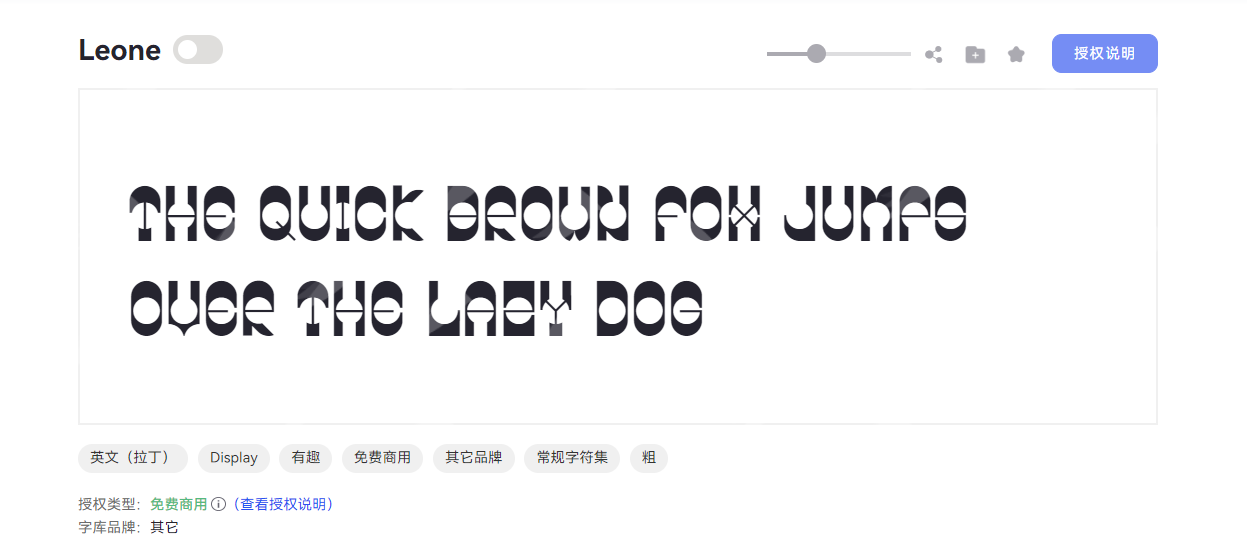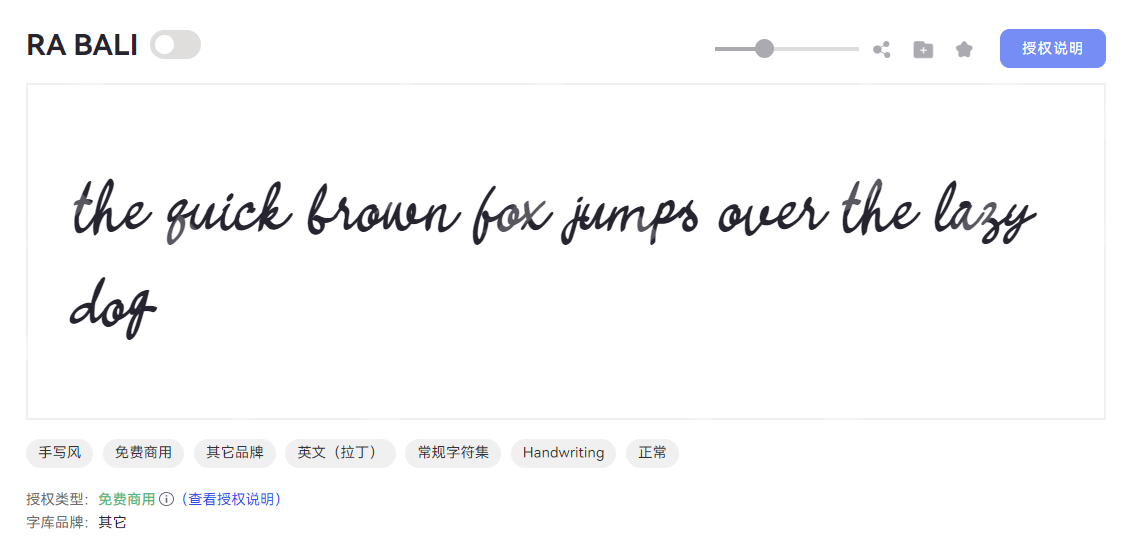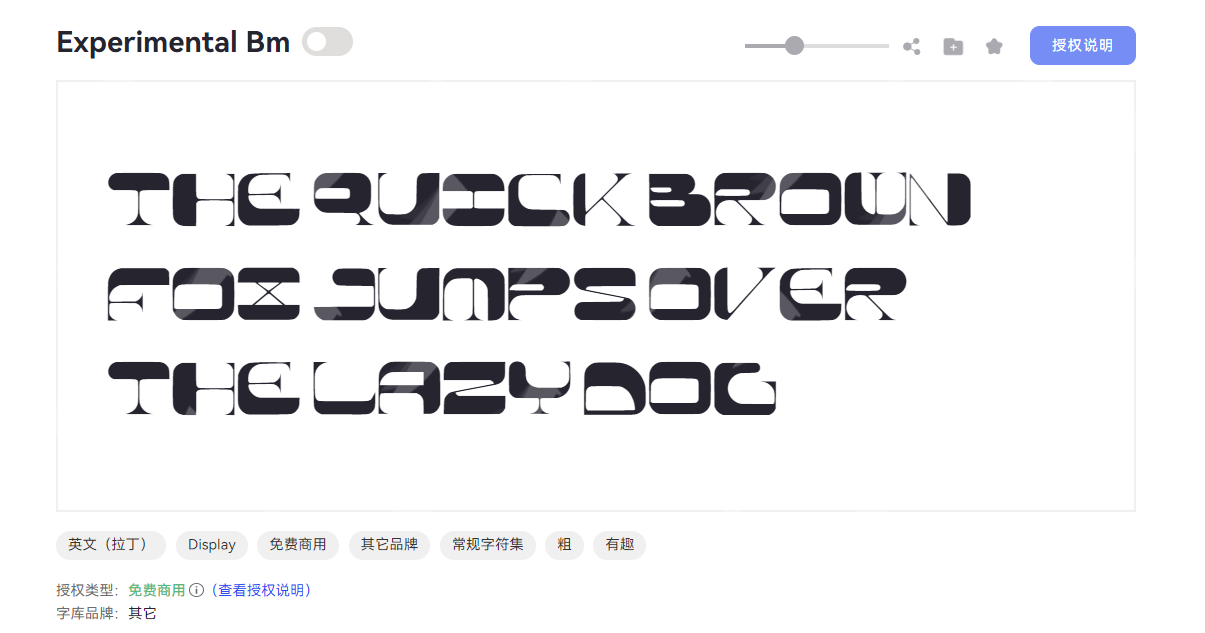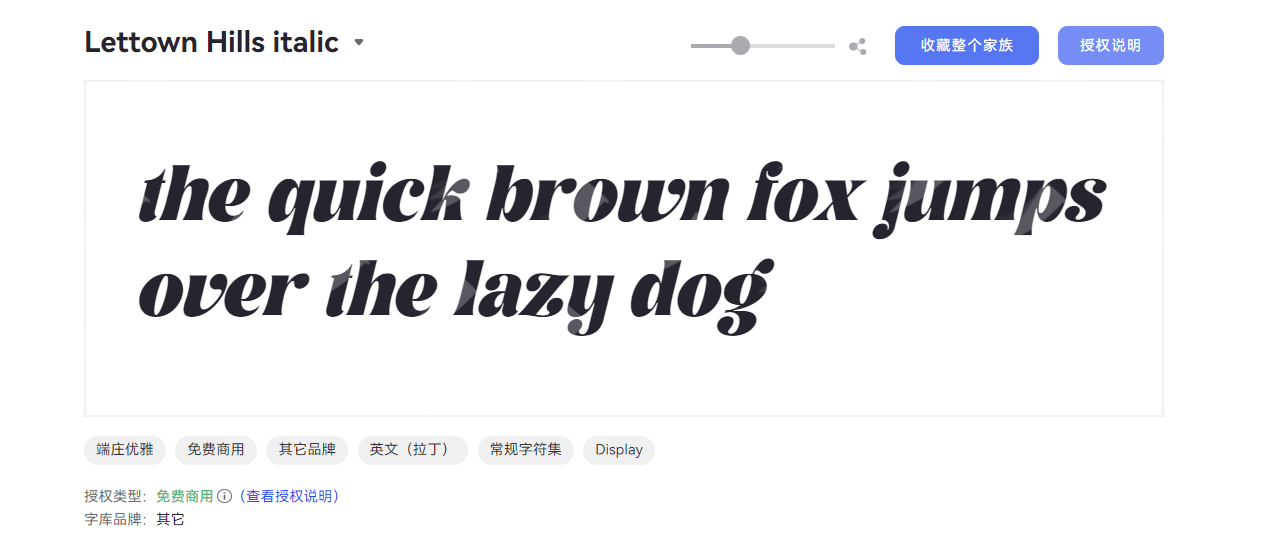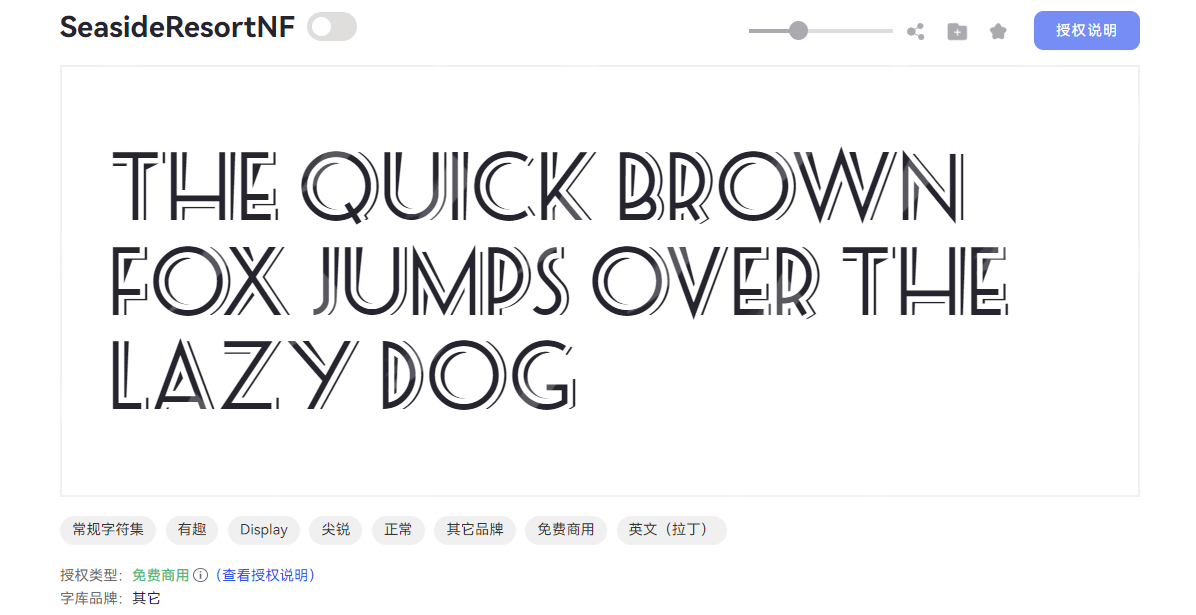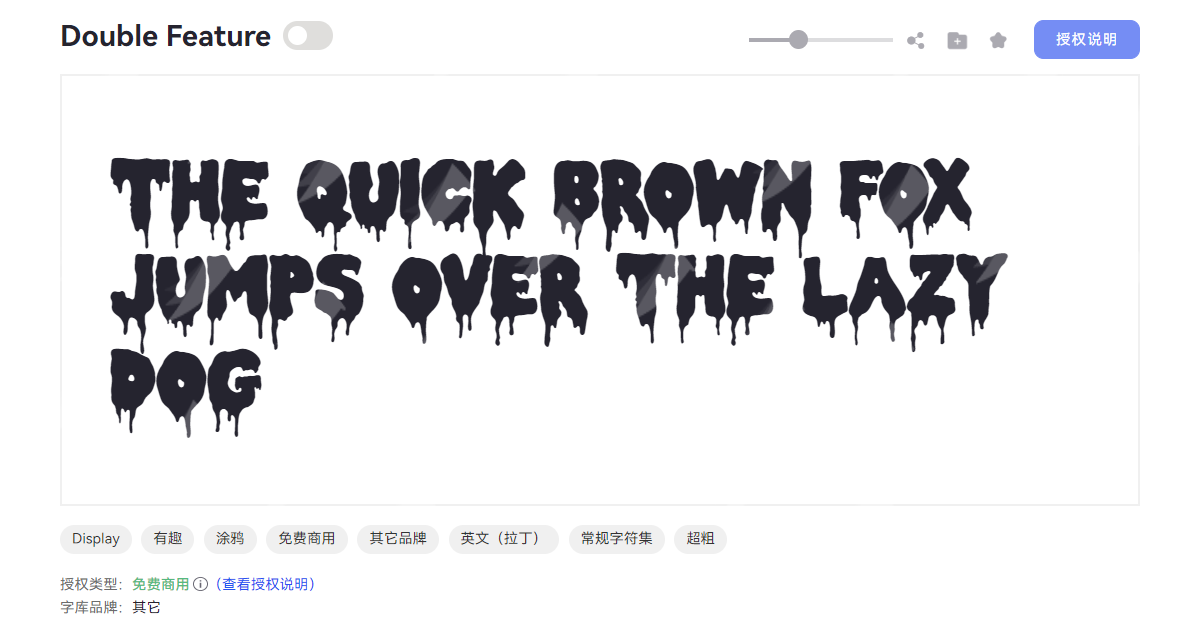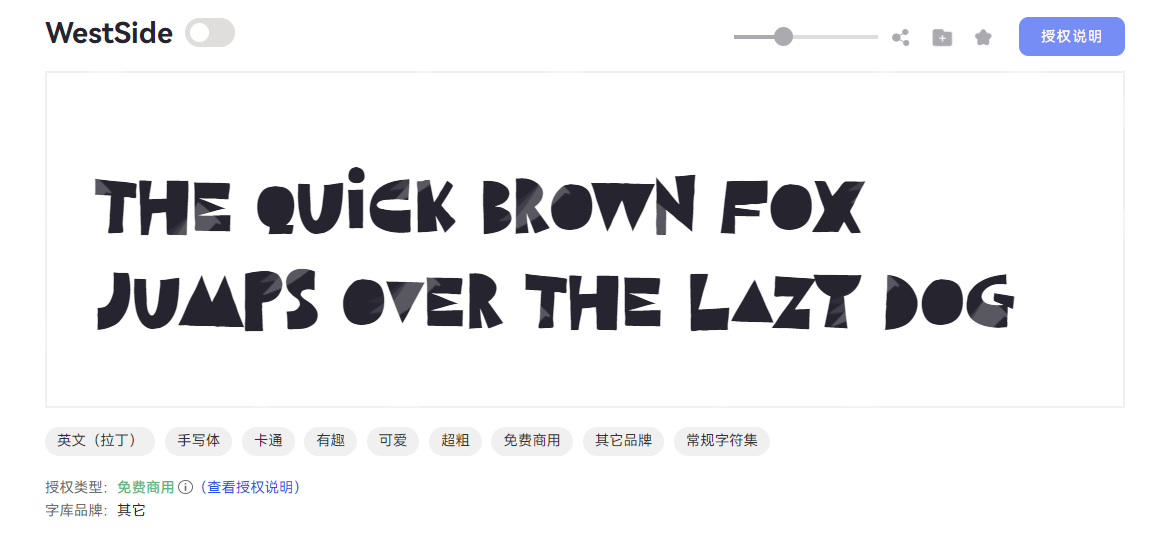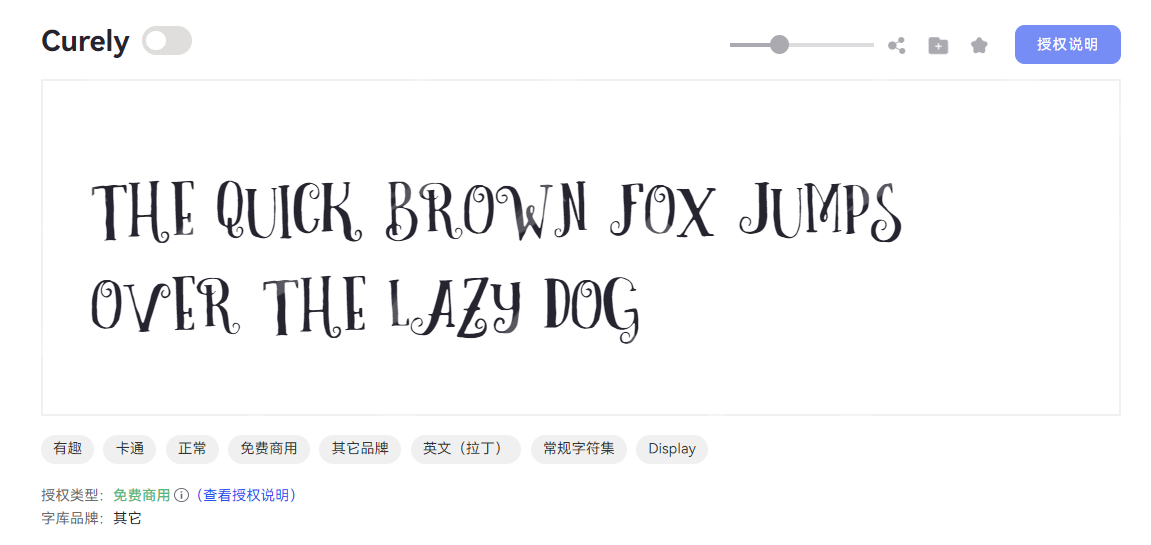
英文艺术字是提升视觉质感的关键因素,通过流畅的笔触和装饰性设计,能增加作品的艺术感。一般来讲,我们在进行海报设计的时候,经常会在中文标题附近穿插一些英文艺术字,用来平衡画面的布局,让海报看起来更具层次感和文艺感。如果你最近也在寻找英文艺术字的资源,千万不要错过我们这份英文艺术字大全!结合字由官网的正版字体资源,给大家整理出了 2026 年最热门的 8 款免费英文艺术字,从新手小白到资深设计师都能直接用,让你的作品瞬间出彩!
1、Leone
字体风格:一款充满趣味感的英文 Display 字体,既大气又不失灵动。
设计特点:修长的字型搭配宽博中宫,让字符在保持粗重笔感的同时,兼具舒展的视觉张力与稳定重心。 最关键的是笔画设计暗藏巧思,粗重均匀的线条以圆润笔触收尾,细节处融入精致装饰元素,笔画连接处的断开处理则打破传统结构,为字体增添几分俏皮趣味。
适用场景:品牌logo、海报设计、创意标题、赛车展览。
2、RA BALI
字体风格:是一款极具个性的英文手写风字体,视觉上给人优雅大气的感觉,以独特的设计细节和实用属性在众多字体中脱颖而出。
设计特点:字形修长舒展,重心稳定居中,中宫松紧适中,既保留手写字体的灵动随性,又保持结构上的平衡感。 RA BALI 在笔型设计上融入了独特的斜切工艺,搭配圆润饱满的笔画端头,让每一笔都兼具利落锋芒与柔和质感。 值得一提的是,该字体的笔画采用断开式连接设计,还原了手写时自然的停顿与呼吸感,同时笔画清晰,避免了可能带来的字体干扰。笔画粗实有力,过渡均匀自然,即使在小字号排版中,也能保持清晰的轮廓与扎实的视觉张力,轻松为设计注入温暖亲切的手写温度。
适用场景:文艺海报、咖啡品牌包装、社交媒体配图、复古信件。
3、Experimental Bm
字体风格:是一款充满个性的英文 Display 字体,,展现出满满的鲜活表现力,吸睛效果很好。
设计特点:字形修长舒展,重心稳定居中,排版整体紧凑有序,视觉平衡感突出。 Experimental Bm 尤其在笔型设计上大有来头,方头笔画搭配利落斜切处理,局部笔画采用“断开”结构,赋予字符灵动跳脱的视觉节奏,细节处的斜切棱角则增添设计温度,让文字成为画面中的趣味焦点。字重饱满粗壮,但某些笔画又极细,看似对比鲜明,杂乱无章,实则展现了强烈的视觉冲击。
适用场景:潮流品牌 logo、潮玩包装、酷炫文创、赛博朋克风海报、游戏背景。
4、Lettown Hills
字体风格:是一款英文手写字体,以端庄优雅的风格立足设计领域,是兼具美感与实用性的最佳选择。
设计特点:从字形结构来看,修长的字型形态搭配宽博的中宫设计,让字体保持舒展大气的视觉效果,确保了基础的阅读清晰度。 笔型设计上,Lettown Hills 圆头笔画的柔和与断开的连接方式形成巧妙对比,圆头笔触增添了字形的温润质感,断开的笔画连接则减少了视觉干扰,让字符在精致中透着利落。而且它拥有均匀的笔画粗细,进一步强化了整体的简约气质,没有繁复的装饰,更能显出现代设计的高级感,是追求个性与实用性平衡的理想之选。
适用场景:电影字幕、vlog 片头、品牌标识、海报正文。
5、SeasideResortNF
字体风格:是一款英文展示型字体,以尖锐有趣为核心风格,兼具个性与实用性。SeasideResortNF 在视觉上营造出夏日感的活力氛围,是打造个性鲜明的视觉焦点的必备英文艺术字。
设计特点:字形修长舒展,重心稳定居中,中宫设计适中,既不过于紧凑也不过分松散,在视觉上保持平衡的同时,自带优雅的延伸感。部分笔画线条加入斜切处理,搭配灵动的尖锋设计,转角处的装饰元素更添活泼气质。这款字体最与众不同的就是,每个字符周围都有一圈极细的笔画,和主体字符的粗细对比柔和不突兀,通过这种微妙的线条联动,呈现出立体阴影既视感。
适用场景:创意标题、卡通海报、儿童读物、音乐节海报。
6、Double Feature
字体风格:是一款充满趣味的涂鸦风格英文艺术字,给人一种随性自由的街头文化感。
设计特点:修长的字型搭配偏高的重心,赋予字符灵动向上的视觉张力,每个字母舒展大气,既有阅读辨识度,又有充足的视觉呼吸感。笔型处理上更是别具一格,方头笔画棱角分明,部分笔画采用断开式连接,配合局部粗细对比,保留了涂鸦艺术的随性与活力。字体结构上稳定平衡,避免了视觉杂乱。Double Feature 每个字符下方都有自然的滴水感线条,完美还原了街头涂鸦时颜料流淌下来的痕迹,自然且富有个性。
适用场景:超酷品牌、潮流广告标题、街头艺术活动宣传、电影标题。
7、WestSide
字体风格:是一款自带萌趣属性的卡通风格英文手写体,以手写体为基底,融合可爱与有趣的风格。
设计特点:WestSide 的笔画设计极具辨识度,以利落的直角线条为骨架,局部融入斜切处理,形成刚柔并济的边缘质感。方头笔画的规整与断开式连接的随性碰撞,在超粗字重的加持下,既保持了粗细均匀的整体协调,又通过笔画间隙的呼吸感避免视觉拥挤,赋予字体独特的节奏与张力,呈现灵动且活泼的视觉感受。
适用场景:儿童读物、萌宠品牌、玩具包装、设交媒体创意配图。
8、Curely
字体风格:是一款以卡通风格为设计理念的字体,充满俏皮与自由的感觉。
设计特点:字体整体字形修长,重心偏高,中宫收紧,展现出独特的视觉张力。 Curely 的笔画采用纤细均匀的线条,尖锋笔画与断开式连接设计形成巧妙对比;某些字符笔画边缘处做连续弯钩处理,在字体规整的基础上,多了一分手写的随性俏皮感,这也是该字体的特别之处。
适用场景:儿童绘本内页、卡通动画、零食包装、童趣风海报。